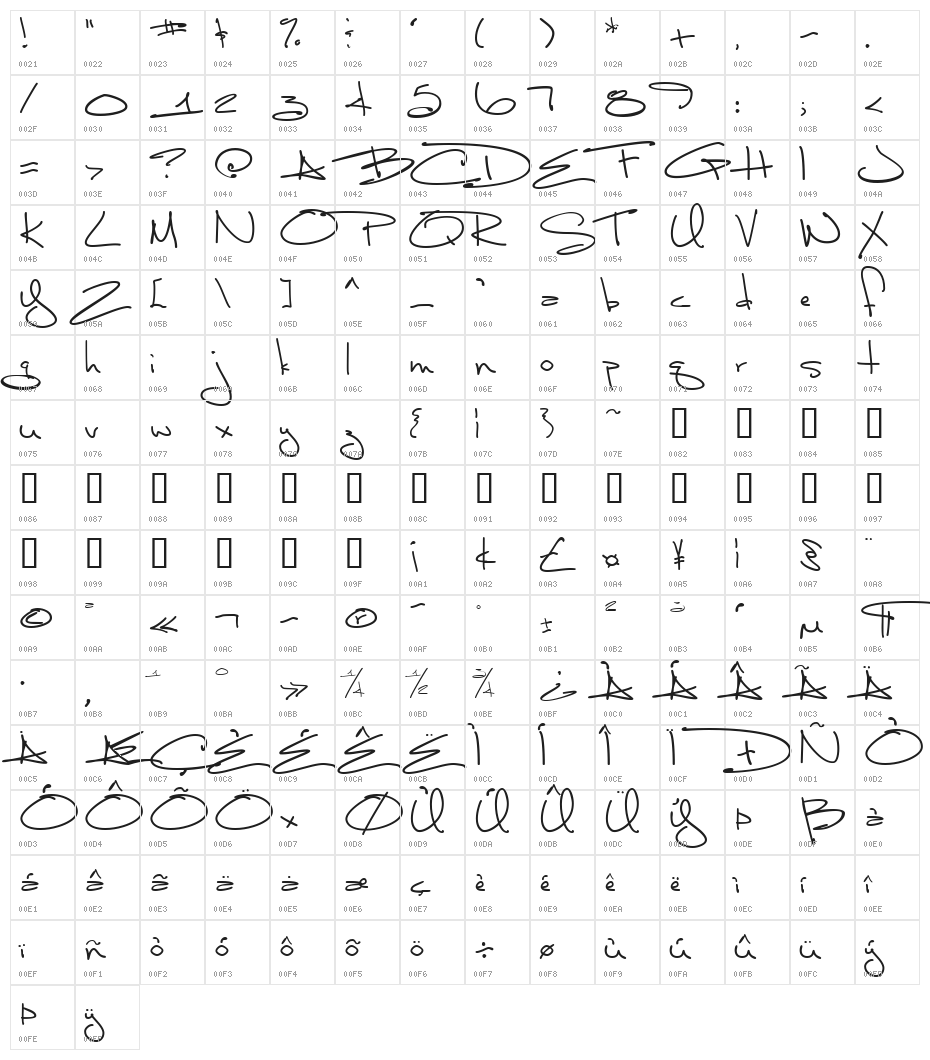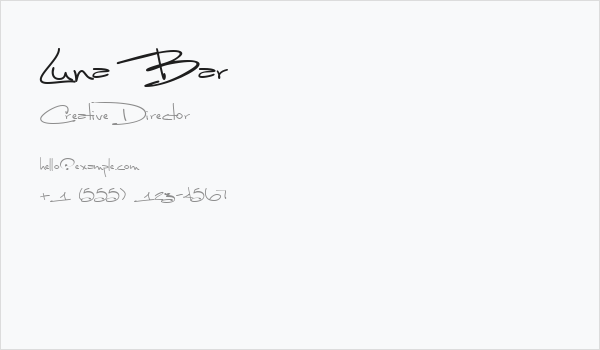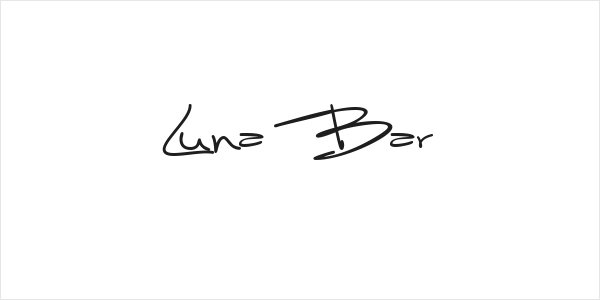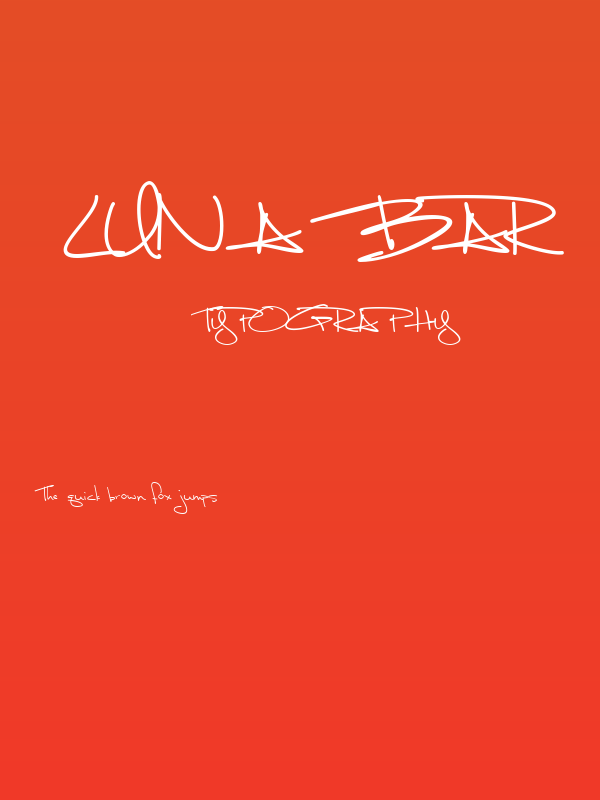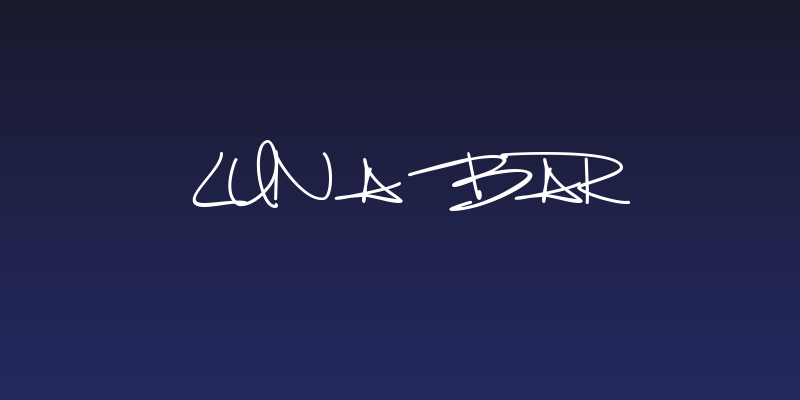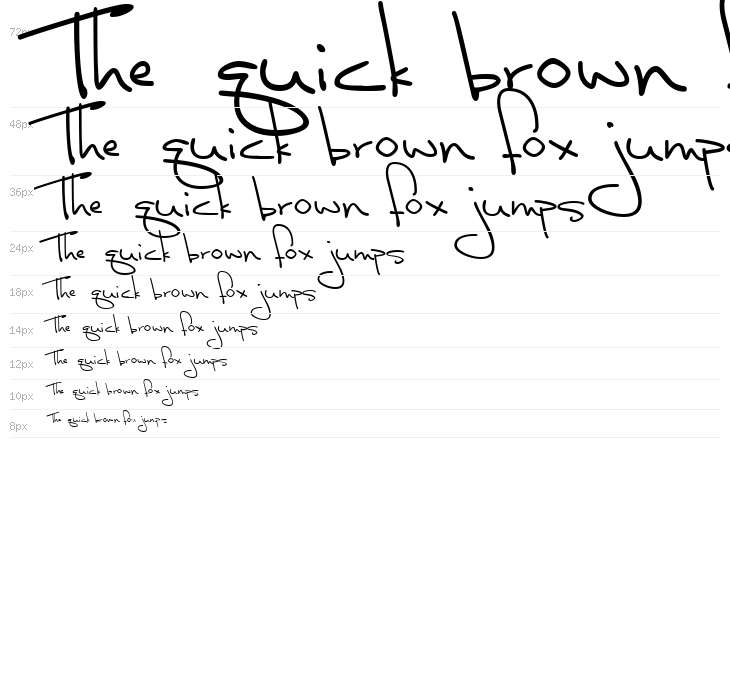
Luna Bar Font
| Anwendungsfall | Logos, Posters, Invitations |
| Vorgeschlagene Projekte | Ideal for creative projects such as greeting cards, invitations, posters, and branding materials that aim to convey a personal and artistic touch. |